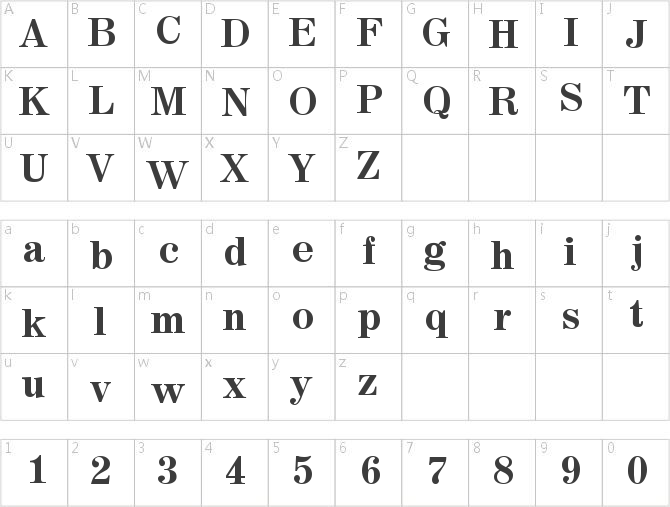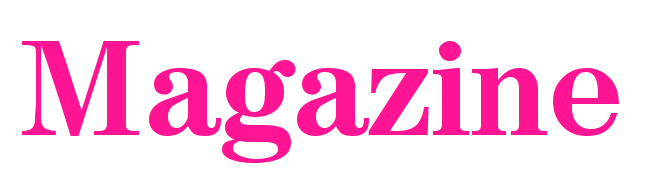
字體名稱(chēng): Magazin
Magazine
Magazine字體字庫(kù)是一款讓人賞心悅目、百看不厭的英文字體,適合各類(lèi)廣告和產(chǎn)品包裝設(shè)計(jì)應(yīng)用,字體大小0.05MB,格式為ttf字體,上傳用戶(hù)是昊天金誠(chéng),作者/版權(quán)方為未知